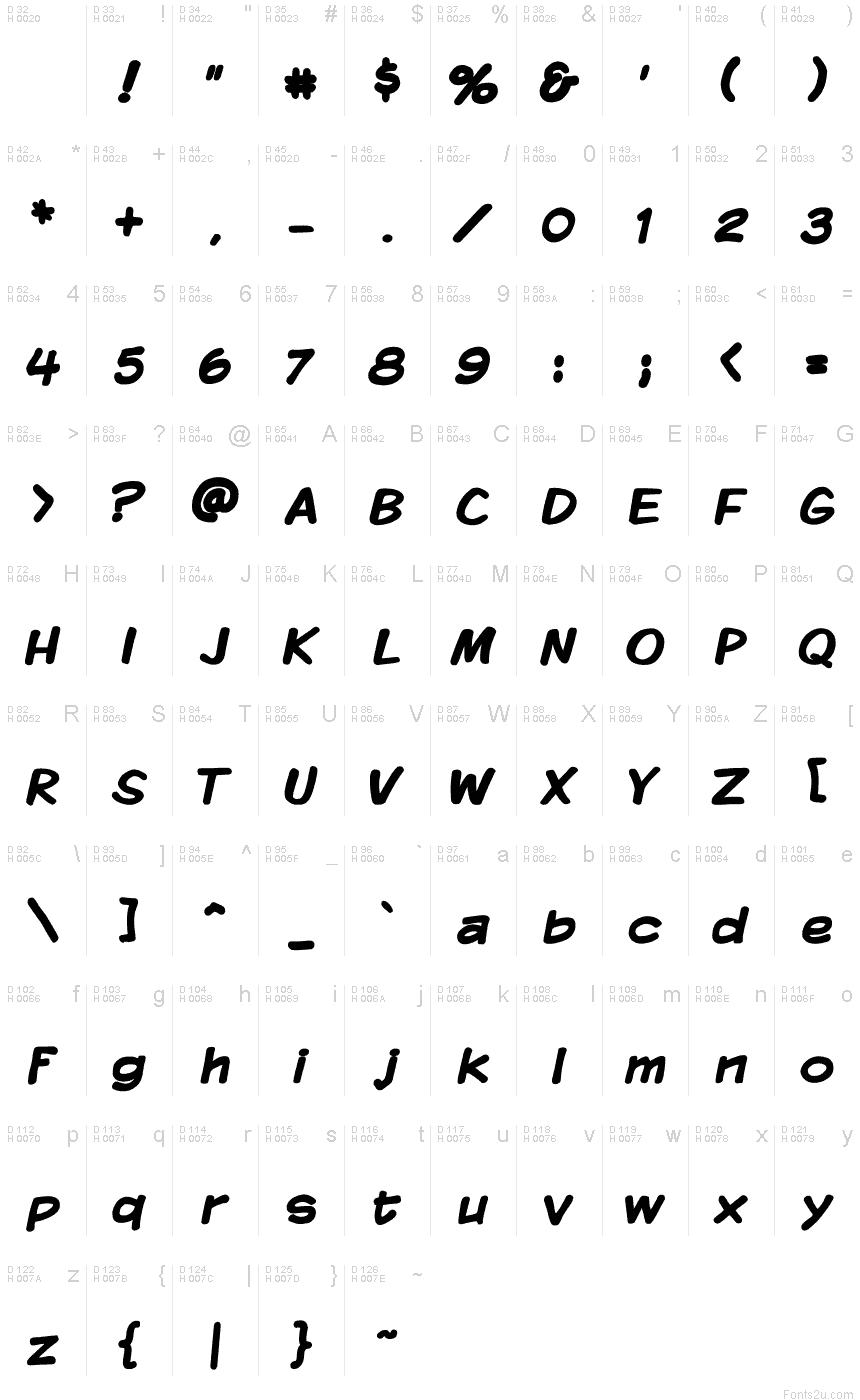
Komika Display Bold autorstwa Wolfbainx & Apostrophic Labs to darmowy krój pisma w stylu komiksowym, wyróżniający się dużymi, soczystymi kształtami i odręcznym charakterem, który wygląda jak wyjęty prosto z powieści graficznej. Litery są grube, zaokrąglone i lekko nieregularne, co nadaje tekstowi dynamiczny wygląd „narysowany flamastrem”, zachowując przy tym doskonałą czytelność. Dodaje charakteru i zabawy każdemu projektowi.
Dzięki Komika Display Bold możesz podkręcić tytuły komiksów, dymki dialogowe, plakaty dla dzieci, miniatury na YouTube, zabawny branding, naklejki czy interfejsy gier. Ten darmowy font błyszczy, gdy jest użyty w dużym rozmiarze; zestaw go z prostym bezszeryfowym krojem w tekście głównym, aby zachować czytelność ilustracji i dialogów, nie tracąc przy tym komiksowego pazura.